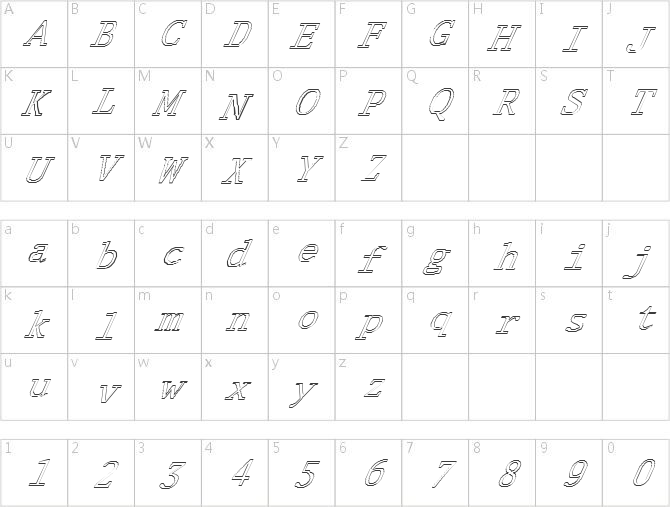
FZ DIGITAL 1 HOLLOW ITALIC
FZ DIGITAL 1 HOLLOW ITALIC字體字庫(kù)是一款讓人賞心悅目、百看不厭的英文字體,適合各類廣告和產(chǎn)品包裝設(shè)計(jì)應(yīng)用,字體大小0.08MB,格式為ttf字體,上傳用戶是曾紹文,作者/版權(quán)方為未知